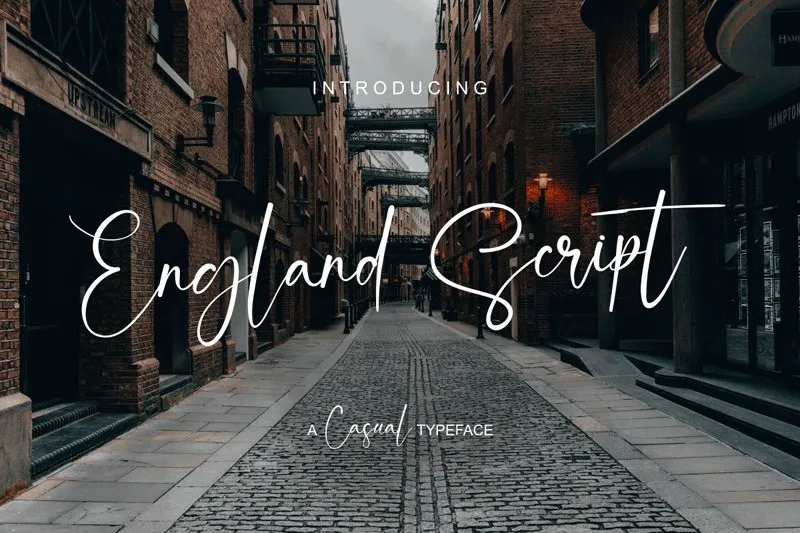
Esta fonte script é inspirada no estilo autêntico das cartas manuscritas escritas por verdadeiros humanos. Ela apresenta curvas únicas e uma textura elegante que se assemelha ao fluxo de um traço de tinta, criando um sentimento intimo e profundo em qualquer texto onde for usada. A 99designs é o designer responsável pela criação desta fonte, oferecendo uma experiência visual atraente para designers gráficos apaixonados por expressar suas ideias de maneiras diferentes. Seja para cartazes, letras de músicas ou editoriais, esta fonte script forneceria um toque distintivo e criativo para qualquer projeto.